如何选择字体?关于字体选择,居然有这么多讲究
你有在知乎上搜过字体推荐吗?你有下过推荐字体包吗?有多少字体装了以后一次都没用过?
以前我也是一车一车地装字体,但很多字体使用后感觉极其不与版面协调。就比如这款被吹爆的康熙字典体,每个字看起来都那么别扭呢?
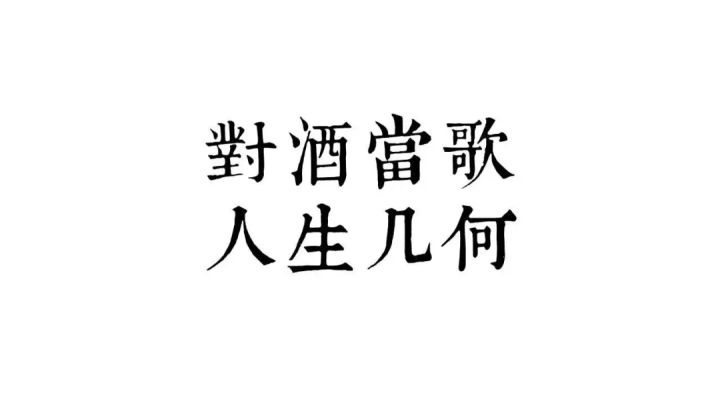
当时我觉得是自己的审美水平太低。事实上,不是知乎上的大神坑我们,也不是字体问题,更不是审美的问题。
是我们忽略的字体它的适用性。
像康熙字典体,从古籍上影印下来的字体,其字形就是为竖排服务的。
抛开适用场景谈字体都是耍流氓!
所以说啊「有哪些好字体推荐?」这是一个不可答的问题。
正确的应该这样问「做PPT(海报、手册……)有哪些好字体推荐?」,而写这篇文章就是为了回答这个问题。
这篇文章的适用范围并不局限于PPT,所以没太多篇幅跟你们抛梗了,内容难免有些枯燥,但请相信,这是一篇干到不能再干的干货。
正式进入主题之前,我们要先摒弃一些在做PPT时秉承的字体选用准则,因为固有经验是我们继续进步的巨大阻碍。
比如下面这段话在很多PPT教程都有说到:
「标宋正黑」相信这是很多人选用字体的准则之一。
在做PPT时,上面的观点总体是没错的,但论据是经不起推敲的,在做其他宣传品时难免被此误导。挑两处来说:
①衬线并不只是为了装饰才加上去的,它可以强化笔画的特征,从而使得阅读和识别更为容易,也可以起到引导读者的视线,让读者阅读文字更加流畅,比较有代表的字体如斯威夫特体。
②黑体「很有冲击力,容易辨认」,这不是用作标题的理由吗?有冲击力的正文你看得进去吗?
衬线并不是决定字体用途的主要因素,那到底是什么?
这就回到主题了——从字体的用途来选用字体。
只要知道一款字体被制作出来的目的,就知道它能用在什么场景了。
①看:字体的艺术性
即用来看的字。这类字体为了体现产品的特色,会丰富(或去掉)字体细节。如广告牌,LOGO。
在PPT里面,就是标题。
这里举谷歌和奥美的LOGO更换的例子。
谷歌作为互联网科技巨头,在2015年将自己的衬线LOGO改为无衬线LOGO,提高颜色明度,字体特色更为现代与活力,体现了一家科技公司的该有风格和文化。
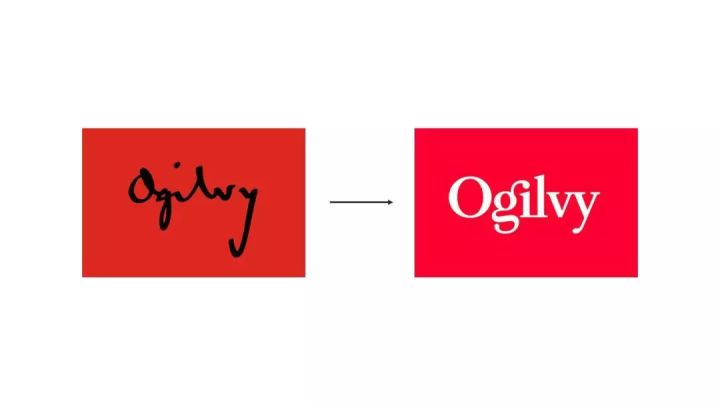
而奥美作为广告业巨头,在2018年将奥美创始人手写LOGO改为衬线体LOGO,弱化了原LOGO所体现的创意感、人文感与艺术感;用新LOGO提高了字体的可认性,强调了灵活,协作与联接的企业文化。
姑且不论两例的LOGO换得是否成功,相信现在的你应该能体会字体的艺术性了。
②读:字体的功能性
即用来读的字,这类字体会尽量去掉字体多余细节,以让读者专注于文字所表达的内容,而不是喧宾夺主,「为自己代言」。
如车牌,道路指示牌。
在PPT里面,就是正文。
优秀的正文字体需要做到结构平衡,重心平衡,灰度平衡……高度的统一性可以让字体本身对眼睛刺激降到最低,而把更多的注意力放在文字表达的内容上。
下图是粗旗黑字体重心调整的前后对比,可以明显感受到,但后者看起来会更加平稳,长时间观看也不会累。
再比如这款叫孔索拉(Consola)的非衬线字体,为了能让程序员在小字号下快速准确地阅读,设计师特意把相似字母做了差异化处理,如 |、i、I、1、l、L和0、O、o。
字体的两大用途讲完了,但现在直接上手去套用,还是会有问题的。这是因为你阅读字体的载体会有各自的局限性。
字体选用的第二板斧就是提前明确字体是在什么设备看的。
①屏显
是指在各类屏幕(不包括视网膜屏及电子墨水屏)上阅读字体,优点是色彩艳丽,但像素密度偏低,所以不适合选用小字重、小字号和粗细对比强烈的字体。
锤子手机发布会也许是所有手机厂商里最突出的。作为高科技公司,大胆使用方正粗黑宋这种带黑体特点的宋体,虽然截图上看字还是有点糊了,但不从众的态度,也正是公司品牌文化的体现。
②印刷
是指在各类印制品上阅读字体,优点是像素密度高,所以对字体的要求也比屏显要低,但字体色彩表现不如电脑准确。
日本街头的招牌字,大多数都是用笔画粗粗的字体,配以鲜艳大胆的配色,吸引路人的眼球。
所以选用字体,一定要注意字体本身的适用范围,用雅黑制作海报,用宋体来演示PPT,而常常导致印刷品的字体死板,演示的字体又模糊不清。
上文说到的功能性与艺术性、屏显与印刷,是一款字体的固有的特性,两两搭配就有了选用字体的四个最常用场景。
而判断字体是否适合某个场景,主要有下面三个要素做参考:
①字重和声量(体量)的概念
字重和声量其实是两个完全不同的概念,有着不同的定义,但为了方便理解,我们可以把它们简单地概括为笔画的粗细。
一般来说,一个字体家族中不同粗细的字体会用字重来区别,如汉仪旗黑字体家族、瑞士黑体家族。
这里也可以证明,黑体并不是专门为了正文用字而存在的。写什么文章能用到旗黑的15个字重135款字体呢?
不同字体间会用声量(体量)来作比较,如小声量的瘦金体与大声量的勘亭流
笔画粗的醒目,适合用于电商网站的banner;远看清楚,所以也适用于大型的广告牌。
笔画细的优雅,适用于屏显标题或小型印刷品(如杂志)。
不粗不细的字体则中性,适合用于正文。
②粗细过渡的概念
仔细观察字体,可以的看到很多字体笔画是有粗细,从粗到细或从细到粗的过程,就叫做粗细过渡(或叫粗细对比)
没有粗细过渡或者粗细过渡较平缓的字体,适用性较广,可以应用于大部分场景。
粗细过渡较强烈的字体,适合作标题,不适合作正文;适合打印,不适合屏显;适合近看,不适合远看。
就算去掉上图右边A字母的衬线,它也依旧不能做屏显正文,因为过细的笔画会造成识别障碍。
字体适不适合在PPT上使用,衬线并不是主要因素,粗细过渡才是。
③字体的可认性及易读性
可认性是辨识单个字符的难易度,也就是「辨认起来的方便程度」。
易读性是辨识整个单词,整个句子,整段文字的难易度,也就是在一大段文字丢给读者时,读者「阅读起来的快慢程度」。
所以可认性是对正文字体的硬性要求,而易读性越好的字体,阅读体验也就越流畅。决定字体易读性的要素有很多:
字体灰度、行字间距、衬线、重心、正负空间,再往下细分还有西文字体的x高度,中文字体的中宫等等。
就以行字间距来作对比,很明显后者阅读起来会比前者吃力。
相信看到这里,大家就可以脑海里建一个坐标系了,把每一个字体对号入座,要用的时候就在对应的象限里找就行了。这里把四个象限的字体做一个简单的总结,可供参考。
屏显正文:多用黑体,以看清楚字为目的,要求具有可认性,字体多清晰锐利。
印刷正文:多用宋体,以阅读体验为目的,要求具有易读性,字体多舒适耐看。
印刷标题:分近看远看,近看宜用强粗细对比或笔画细字体;远看宜弱粗细对比或笔画粗字体。
屏显标题:对介质本身要求较低,具体按产品调性决定。
当然如果你嫌这样做效率太低,我们可以把先风格相似的字体找出来,打个包一车一车地放进坐标系里。这就是下面要讲的字体分类。
其实最基本分类大家都会了,无非是衬线非衬线。现在我们就可以再细化一下了,先从英文字体开始吧。
①英文字体分类
为了方便理解,我把英文字体大致分为衬线体、非衬线体、手写体和花体,其中衬线体分三小类,非衬线体分三小类。
衬线体
支架衬线体又称旧式体,代表字体——Garamond。
粗细过渡相对缓和,拥有不可见性而不会读者分散注意力,强调文字表达的内容,显示大量文字的最佳选择。
发丝衬线体又称现代体,代表字体——Didot。强烈的粗细过渡,高雅、冷酷,适合做杂志标题。迪奥、阿玛尼的LOGO都是Didot的变体。
板状衬线体又称粗衬线体,代表字体——rockwell。几乎没有粗细过渡,区别于一般衬线体的古典正式,粗衬线体更有亲近现代的感觉,最初是为适用广告牌等场景而诞生,所以非常适合做海报标题。
非衬线体
古典无衬线体,又称人文主义体,代表字体——optima。
旧式体与无衬线体相结合的过渡字体,兼顾前者的典雅美观与后者的冷静理性。
过渡无衬线体,又称标准无衬线体,代表字体——helvetica,受现代主义影响而诞生的产物,最大的特色就是没有特色。引用迈克尔·布雷特的一段评价:「它们存在着,仿佛原本就是环境的一部分,他们就好像空气,或是重力」。
现代无衬线体,又称几何体,代表字体——Futura。承袭现代主义的设计理念,其主要特点就是要按照严格的几何比例,表达文字的美感,因此适合做标题,用在大量正文会稍腻。
手写体、花体
可以简单理解为写出来的字体和画出来的字体,应用场景相对较单一如书信、儿童书等,排版难度也较高,所以就不作详述了。
当然上面的分类只是提倡的分类方法,实际上西文字体分类要复杂得多。比如我们熟悉的Times new roman,它实际上属于旧式体与现代体之间的过渡字体。
但我们给字体分类的目的是更好的使用它们,不是为了分类而分类,所以我更愿意把它并到旧式体上面去。
②中文字体分类
中文字体目前还没有更系统的分类,一般沿用书法字体的分类,这里会重点讲一下宋体和黑体。
篆书、隶书、草书、行书、楷书
篆书瘦劲挺拔、隶书古朴典雅,草书纵任奔逸,行书自由流动,楷书方正平直。
它们都属于手写字的范畴,有特定的应用场景,不建议乱用。
特别注意的是楷体,它的结构其实「左低右高」的。观看时视线也会因此受到影响,所以并不是正文阅读的最好方案。
日本称为明朝体,很多PPTer认为宋体被人用滥了,所以会排斥这款字体,甚至会说宋体是一款「垃圾字体」,这是不对的。
宋体字形优雅端庄,是最中国风的字体,而且款式远比黑体要丰富。如果对自己的排版能力有自信,就应该大胆去尝试一下,日本也有大量的设计作品可供参考。
宋体的用途主要依据粗细过渡来区分。
过渡强烈,用作标题,如特雅宋、清刻本悦宋;
过渡平缓,用作正文,如报宋、书宋、刊宋;
其中也有针对屏显优化的,如悠宋、思源宋。
日本称为哥特体,是最年轻的一类字体,黑体字形现代简洁,尤其在低分屏下显示效果优秀。
黑体的用途主要依据字重或声量来区分。
大字重大声量,用作大型印刷品(远看)的标题,如造字工房力黑
小字重小声量,用作屏显或小型印刷品(近看)的标题,如方正兰亭超细黑
正常的字重或体量,用作正文,如冬青黑、思源黑
其中也有针对屏显优化的,如雅黑、悠黑。
黑体用作正文其实是对低分屏的妥协,因为在同等字号下,少了很多细节的黑体会相比其他字体会字面更大,显更清晰。
原Windows默认字体微软雅黑作为彻彻底底的屏显字体,更是妥协中的妥协,在同等字号下,雅黑的中宫(即下图灰处)会比一般的黑体字体再松一点,但跟眼距长显弱智是同样道理,中宫太放了就会显得字有点呆滞,尤其在印刷品上。
现在微软把windows10的默认字体弃雅黑而用等线,一来现在的屏幕分辨率提高了,二来字体渲染水平提高了,有能力驾驭这种中宫稍紧,带有喇叭口的黑体了。
而冬青黑体(Hiragino Sans GB)包括瑞士黑体(Helvetica)更是黑体中的翘楚,因为他们在保证字体结构稳定美观的基础上,屏显、印刷上,无论大小字号都有很好的显示效果。
怎么样?看到这里,你会用字体了吗?
文章的最后,当然是送福利,30G字体包?当然不是啦,是我认为获取字体最好的地方。
我知道有很多类似「字由」的字体管理软件可以安装字体,网上也有大把资源可以下载,但我还是建议去官网下载,原因有二:
①免费
这也是最实在的,其实现在很多字体公司都有免费的个人非商业版授权,我知道的就有方正、汉仪、造字工房,既然可以免费用正版字,又何必冒着中毒的风险去下盗版呢。
②字体介绍详尽
字体公司是字体的父母,他们肯定最了解自己的孩子了,也知道他们的特长在哪里,看他们字体介绍能更好的了解一款字体的用途。
常用免费字体网站
方正字库:
方正的宋体特别能打,如果找不到想用的宋体,可以去方正看看。
汉仪字库:
支持按照场景和字体特色来搜索字体,善用搜索能省去不少找字体的时间。
造字工房:
造字工房几乎没有「正经」的字体,每款字体都非常有趣,如果想找有特色标题字体,可以在这里找。
说了这么多,相信大家对字体版面设计更进一步的理解了。如果现在觉得有点乱也没关系,以后用的时候会更凌乱的。因为上面说的只能作为参考,字体排版设计中有太多的反例了。
比如我说笔画粗的字体适合远看,实际上如果笔画太粗了,远看反而会看不清,因涉及到了字体的负空间,这里就不做深究了。
再比如说把草体、楷体和宋体放在一起看,是不是很杂乱?
但日本人就是这样看的,而且阅读体验还不错。以前德国人也用哥特体当正文字体,照样能读得飞快。
所以说字体选用并没有什么绝对对或绝对错的,与其相信权威不如相信自己的眼睛,让它们能表达清楚你的想法,这才是最紧要的。